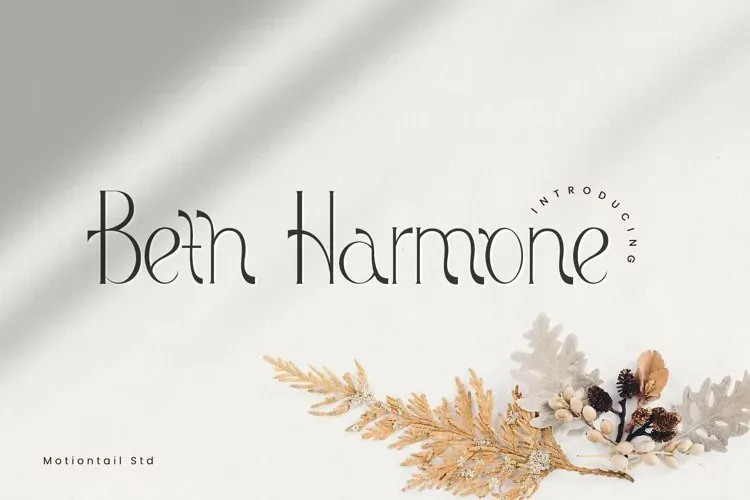
Beth Harmone Font – Download Grátis
A Beth Harmone Font é uma elegante tipografia serifada que oferece um toque luxuoso a cada letra graças às suas tiras finas. Esta fonte moderna e sofisticada cria um design único, tornando-a irresistível para quem procura estilos de design inovadores e carismáticos. Além do seu charme individual, essa fonte também apresenta uma característica simples mas luxuosa que o torna ainda mais apelativo. Perfeita para designers apaixonados por gráficos que buscam uma combinação única de modernidade e sofisticação, a Beth Harmone Font não é apenas um recurso adicional ao seu trabalho; ela transforma-o em algo extraordinário, redefinindo o padrão do design gráfico.